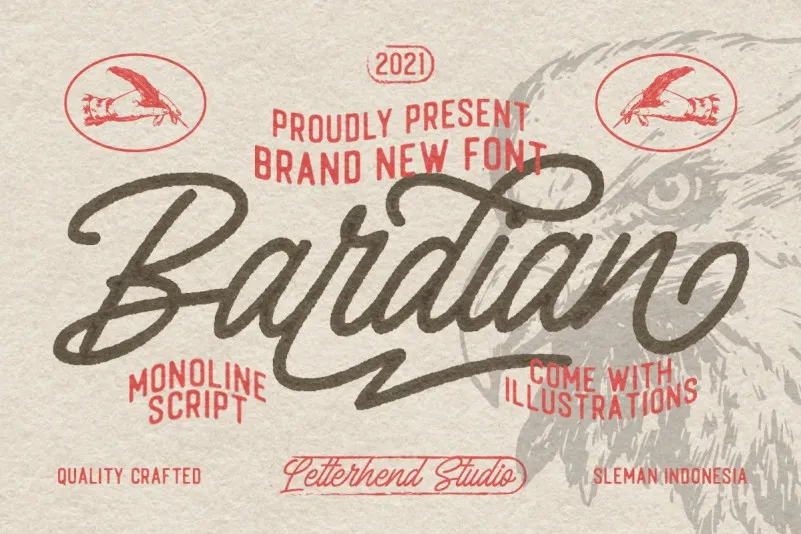
The Bardian Font – Download Grátis
A fonte “The Bardian Font” é uma escolha ideal para quem busca dar vida a seus projetos com um visual elegante e inovador, sem perder o encanto vintage que tanto combina com a estética contemporânea. Esta tipo de fonte foi criada através do processo manual de escrita ou escaneamento (sket), dando-lhe uma aparência autêntica e quase realista, que convida os designers a experimentar formas mais elaboradas e detalhadas. Com seu estilo bold e script, The Bardian Font é perfeito para aplicação em projetos como logotipos, headlines ou sinais de identidade. Seu formato também torna-a uma opção ideal para criações formais que incluem convites, etiquetas, selos, capas de livros, cartões de saudação, embalagens, revistas e novels, além dos ambientes de marketing como materiais de embalagem, maquiagem ou estilismo, papelaria e até mesmo produtos de moda. A inclusão adicional de 10 objetos detalhados desenhados à mão oferece mais flexibilidade ao designer, permitindo adaptá-la a um número ainda maior de aplicativos possíveis. Além de suas aplicações nos campos da design gráfico convencional, The Bardian Font também traz o poder de ser usada em projetos onde um visual diferente e único pode dar um toque especial à produção. Seja para celebrar uma ocasião memorável ou estabelecer uma conexão única com os consumidores através do uso da sua identidade visual, “The Bardian Font” é uma escolha atraente que certamente enriquece qualquer projeto.